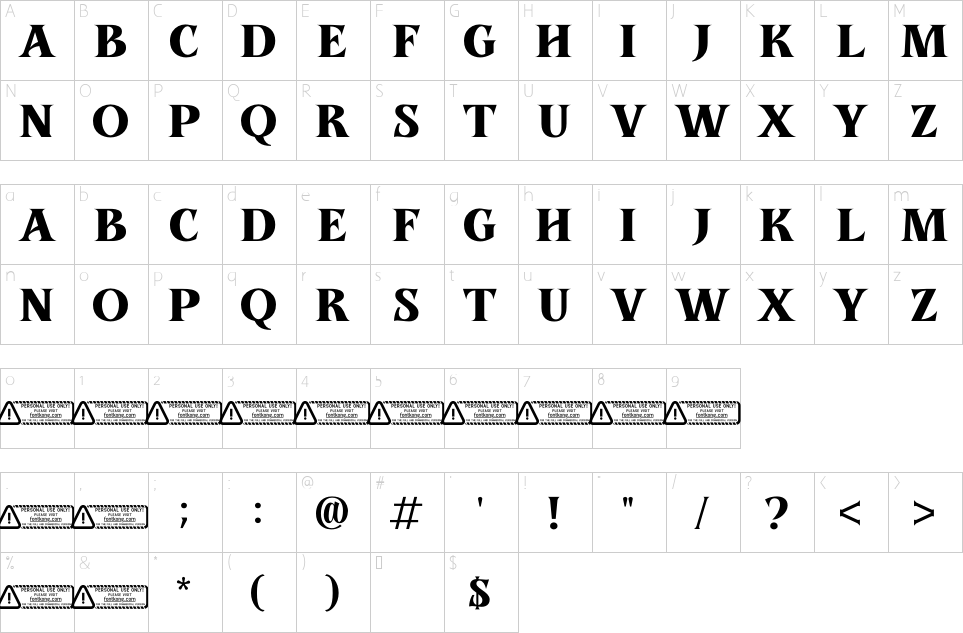
Descubra Aosta, uma elegante e versátil fonte gráfica disponível de graça para download em seu sistema operacional Windows ou Mac. Desenvolvida por Font Kong, esta fonte oferece um toque sofisticado aos seus projetos. Não é à toa que Aosta se destaca, já tendo sido baixada por 324 usuários apaixonados. Seja para incorporar em sua identidade visual, criar rótulos atraentes ou finalizar seus projetos de design, Aosta é a escolha perfeita. Seja você um designer gráfico iniciante ou um profissional, não deixe de experimentar Aosta e revolucionar sua paleta de fontes.